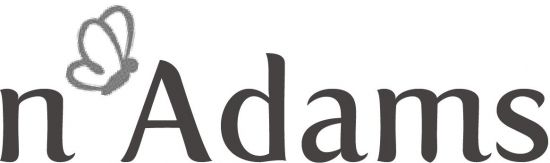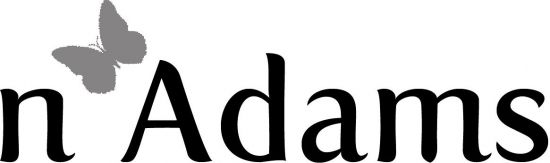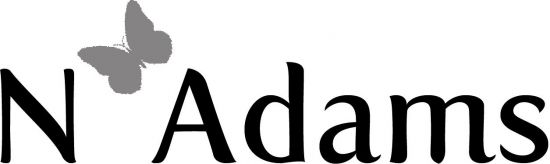
Wortmarke für Modelabel. Wie findet ihr es?
ich hänge gerade etwas bei der Gestaltung einer CI. Kurze Erklärung:
Das Logo (Wortmarke) ist für einen Schneider, der Damenkleidung herstellt. Die Sachen sind verspielt (Blümchenmuster) und bunt. Der Schneider selbst auch! Er hätte gerne seinen Namen mit eingebaut (Er heißt Nathan Adams).
Das ganze soll nicht zu streng wirken, aber wie immer gut einprägsam sein.
Als Schrift habe ich die Fertigo gewählt, die ich sehr schön finde. Auf dem Bild sind ein paar Variationen zusammengestellt. Mich würde eure Meinung interessieren und für Kritik bin ich auch dankbar. Die Farbgebung ist derzeit noch zu vernachlässigen.
keinen Apostroph, oder was das da ist - sieht aus wie "n'Abend".
Das hochgestellte n gefällt mir gar nicht. Warum nicht einfach n*adams? Wobei das * ein "gestickter" Schmetterling sein kann.
so auf den ersten blick sprechen mich die farben überhaupt nicht an.
grau und orange und vorallem diese abstufungen. bei den hochgestellten
buchstabnen würde ich immer in versuchung gerraten einen sinn dahinter
zu finden. den finde ich leider nicht. :?
Ok, keine Hochstellung! Keine Farbe.
ähm, du musst das nicht gleich so machen, nur weil ICH es gesagt habe,
es ist immer nur mein persönlicher geschmack. du bist der designer,
du verkaufst das ding dem kunden und ER ist der kunde ... nur so als tipp ;)
ok, sieht schon ruhiger aus. der schmetterling wirkt noch etwas steif, vielleicht
etwas schrägstellen. hast du auch einen seitlichen schmetterling? der jetzige
sieht etwas untypisch aus, was seinen flugrichtung betrifft.
Den Schmetterling als Assoziation entlang der Richtung "leicht, flatterhaft, verspielt, luftig, ungefährlich, zart und so weiter" finde ich passend. Nur wirkt der Aufblick etwas statisch, da ist bestimmt mehr drin. Im Profil etwa ein Schmetterling, der an der Wortmarke schnuppert.
Je nachdem, wie klein das ganze angebracht wird, schrumpft natürlich der Schmetterling zum Fleckchen.
Fertigo finde ich auch passend. Aber "n'adams" darf nicht nach abgekürztem "Nostradamus" aussehen, das wäre eine unerwünschte Assoziation. Vielleicht hilft da ein großes 'A'?
An Nostradamus hatte ich garnicht gedacht. :-)
Ok, die Schmetterlinge haben beide keinen Pepp!
Meinem Logikbedürfnis widerstrebt es ein bißchen, daß das N klein, das A aber groß ist, da ja beide die Anfangsbuchstaben der Namen darstellen. Aber das ist eine logische Frage, die der graphischen Lösung vielleicht widerspricht. Nur mal so gesagt, um die Sache zu komplizieren.
Meinem Logikbedürfnis widerstrebt es ein bißchen, daß das N klein, das A aber groß ist, da ja beide die Anfangsbuchstaben der Namen darstellen.
Und meinem widerstrebt es total.
Für mich sind deine allerersten Entwürfe dahingehend spannend, dass ich ständig die Assoziation zu "madam" aufzubauen versuche ... nathan, mnAdam, Damenschneider und so weiter ... einfach so dahingeplappert, jetzt mal.
8) und für die Hardcore-Biologinnen unter uns: spießt du den flachen Schmetterling einfach mit einer Nähnadel an den Adam 8)
ne ne, es ist schon das große n vom vornamen. abgesehen von der logik, sieht es dann aber noch besch... aus (langweiliger)!
die assoziation zu "madam" ist eher unbeabsichtigt. will nicht wissen, wieviele labels ein madam im namen haben!
…abgesehen von der logik, sieht es dann aber noch besch... aus (langweiliger)!
Daß Logik und Ästhetik eine Einheit bilden würden ist mehr, als man in diesem Leben erwarten kann.
…ständig die Assoziation zu "madam" aufzubauen versuche ... nathan, mnAdam, Damenschneider und so weiter ... einfach so dahingeplappert, jetzt mal.…
Ich muß bei diesem abgetrennten n immer an N’Dragetha denken. Oder heißt das ’Ndragetha?
mafiamode für frauen? dann sollte ich eine pistole anstatt einem schmetterling wählen! :lol:
Und einfach alles in verspielten Großbuchstaben?
Oder Nathan A. statt n.adam? (Na dann, Madam, zum Adam, zum Nathan Adam, zum Nadel-Nathan Adam!)
Ästhetik, Logik und Klang. Kurz aber vollständig, originell und unverwechselbar, einfach und raffiniert zugleich. Und alles gestern, und bitte fast für lau.
Tja, das scheint mir eine ganz normale Herausforderung in Eurem Berufsfeld. Respekt, allen Ernstes, das wäre mir zum Brotverdienen zu anstrengend.
Mit Minutenzeichen vorn? :mrgreen:
... und einem "n" mittendrin mehr (nicht unbedingt in Zollzeichen).